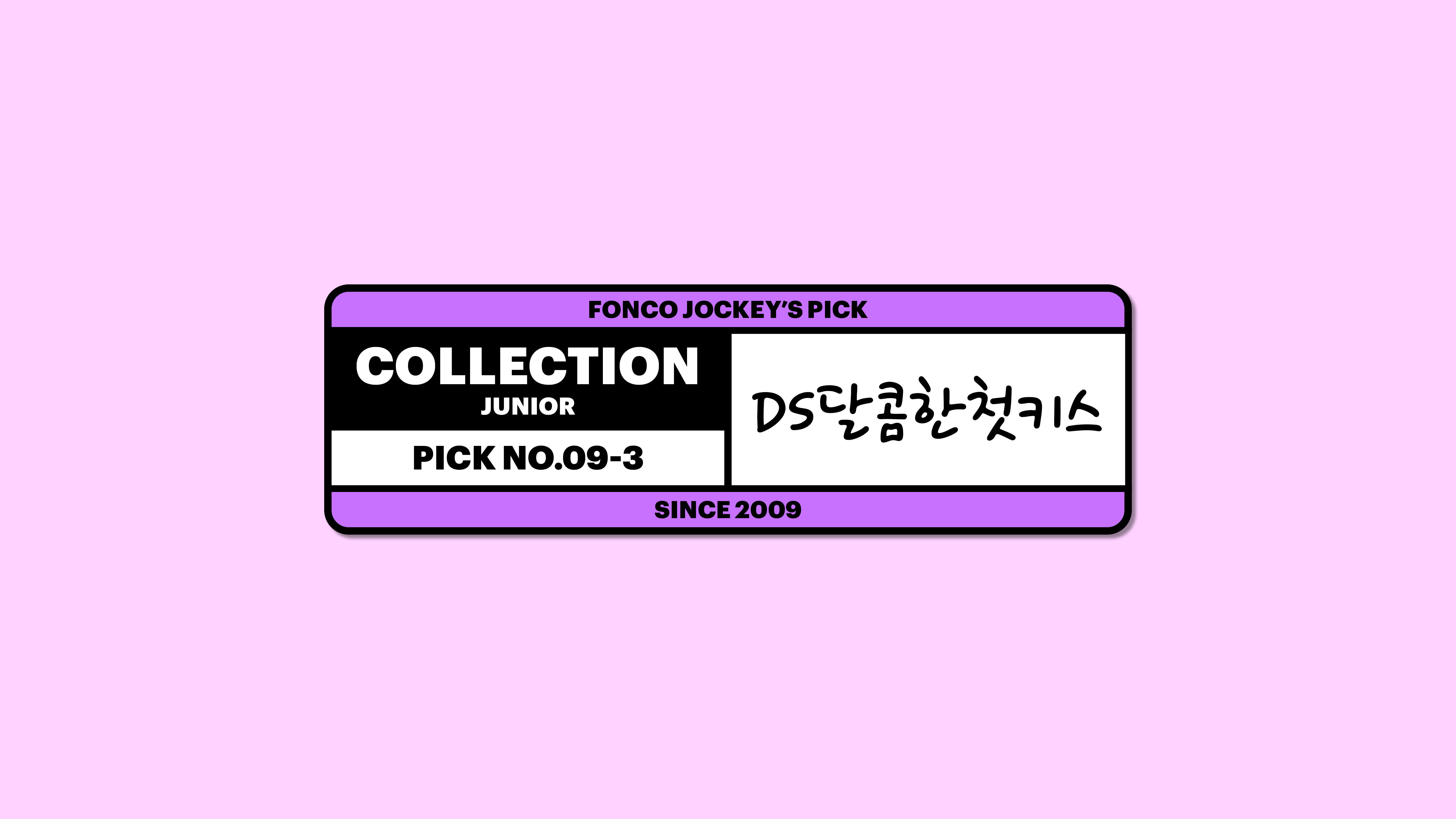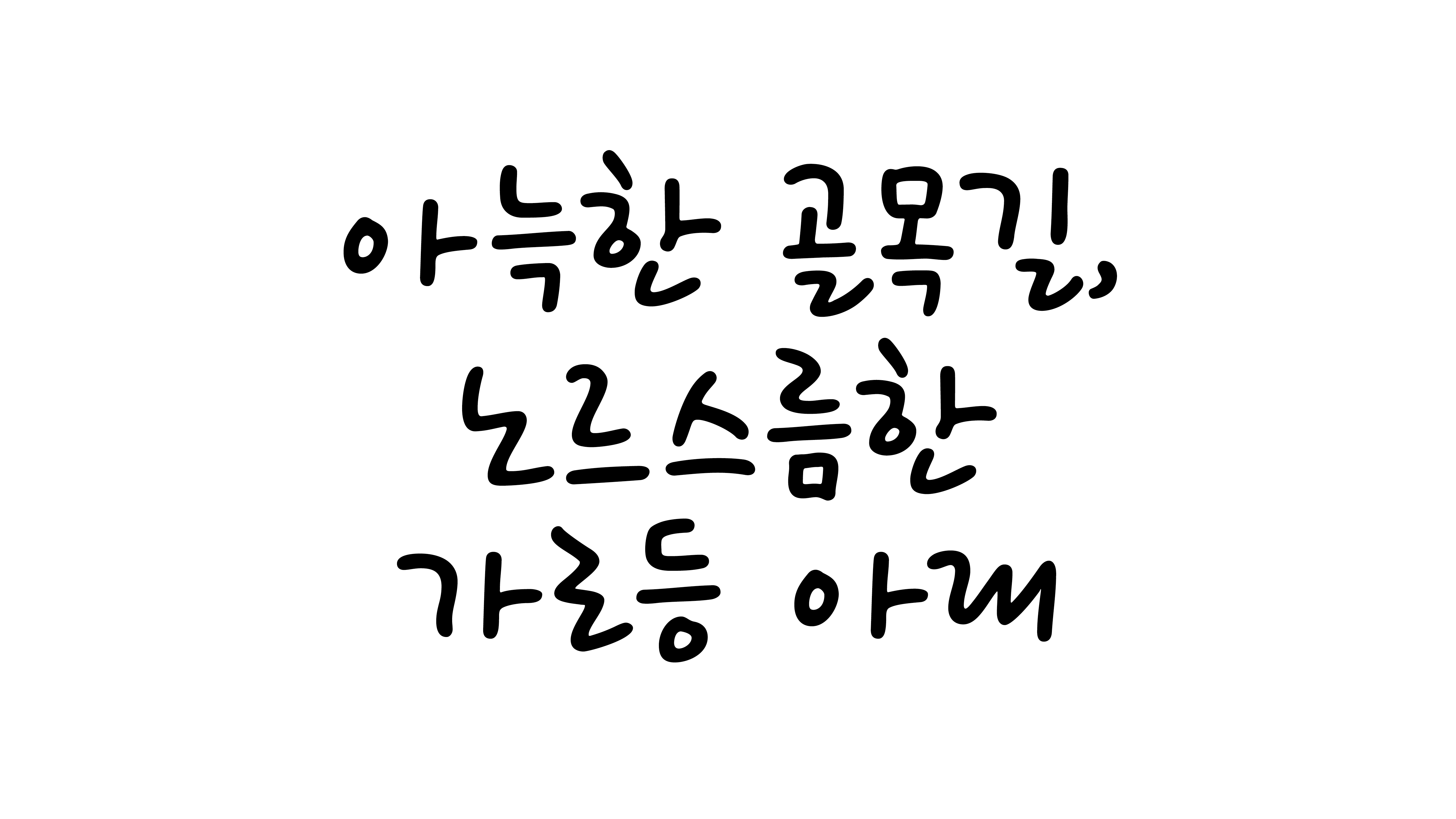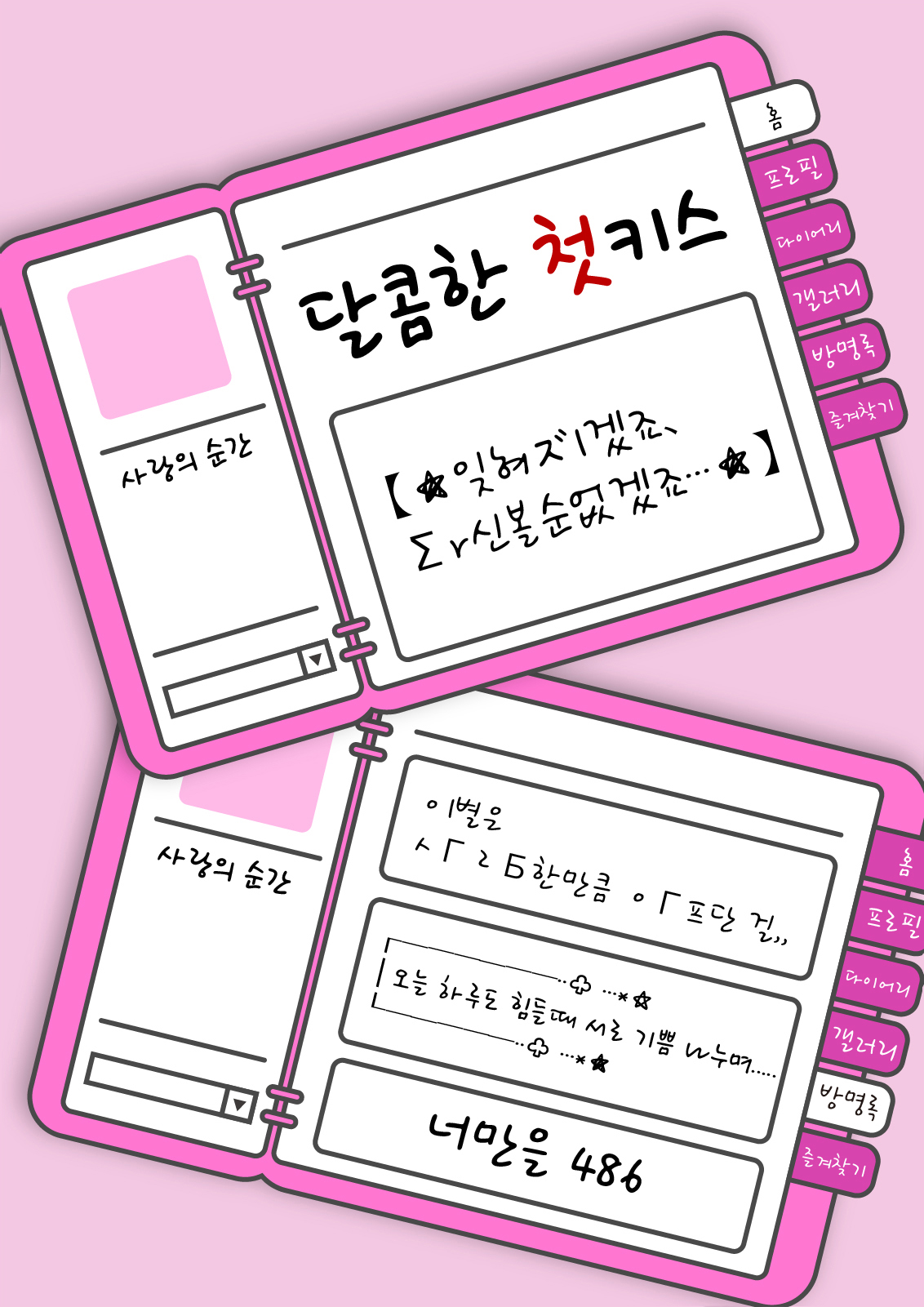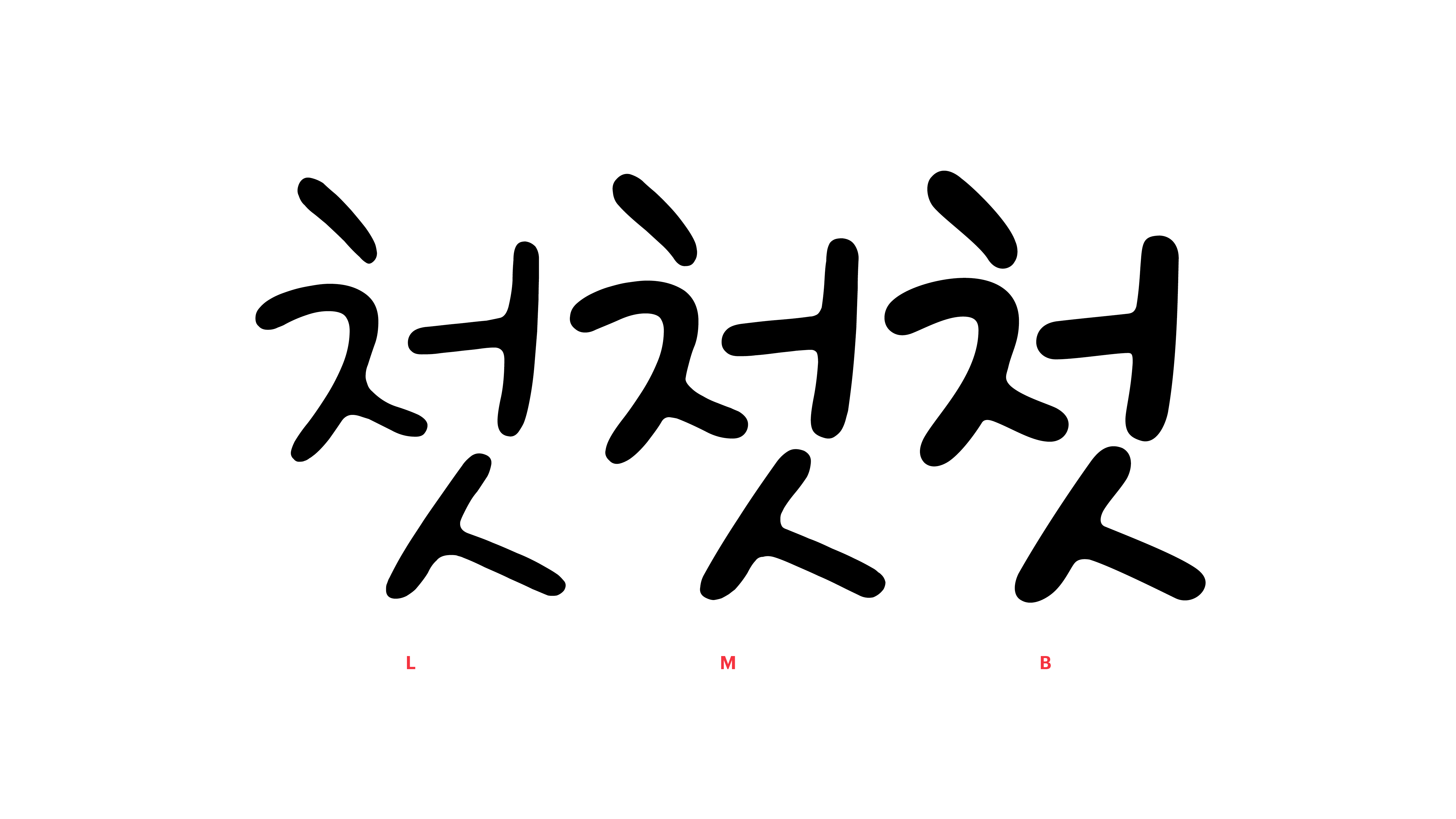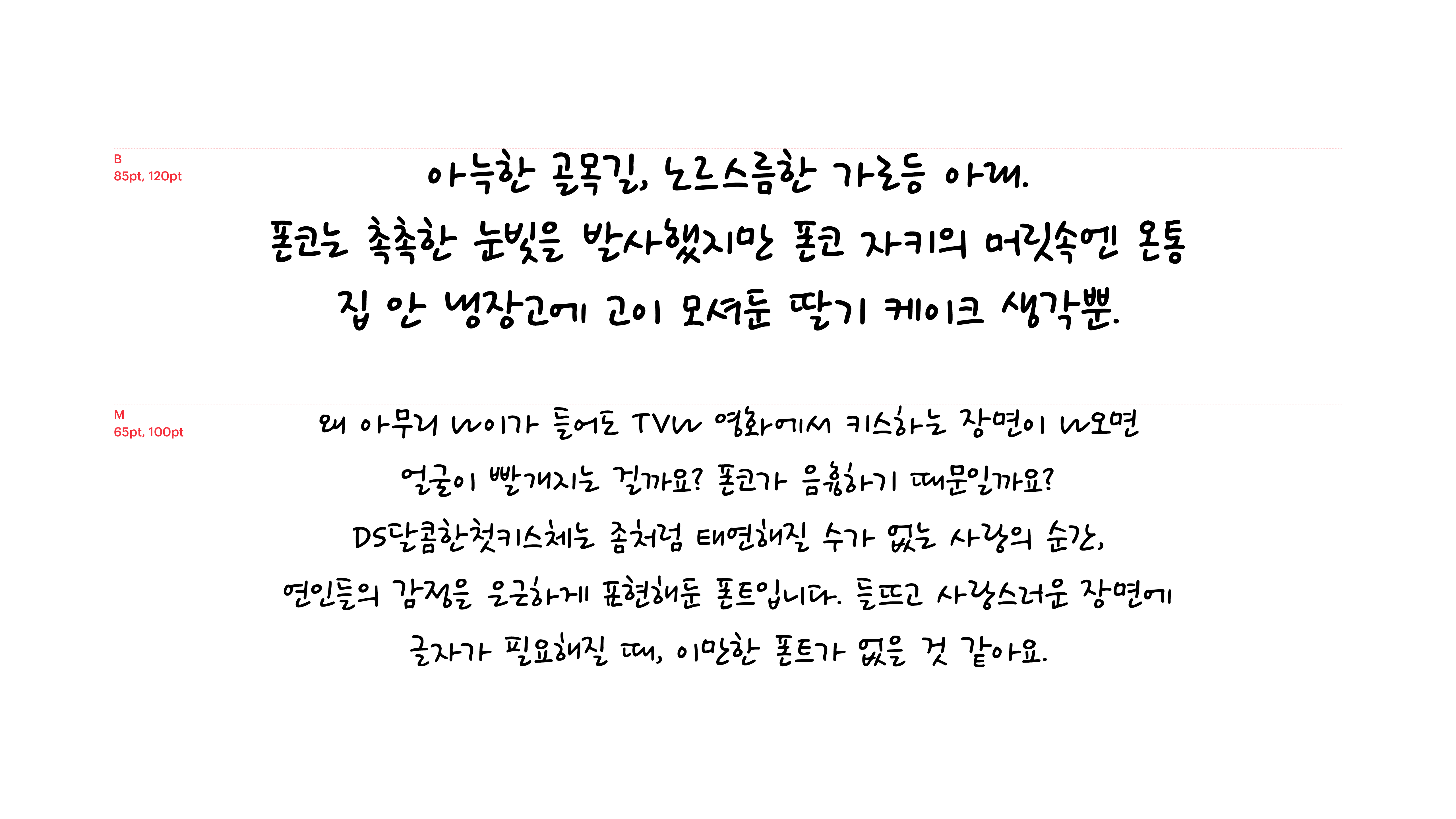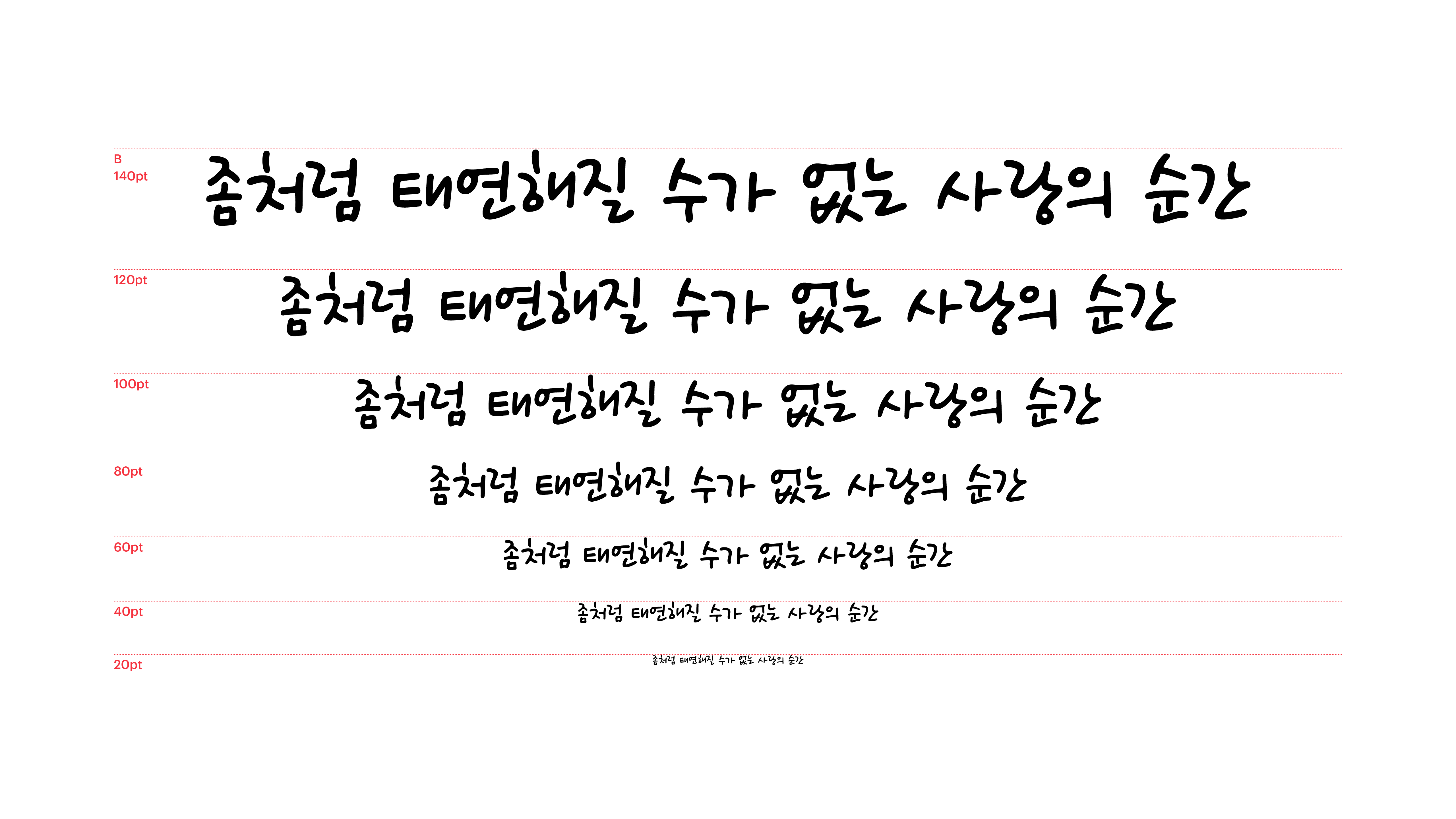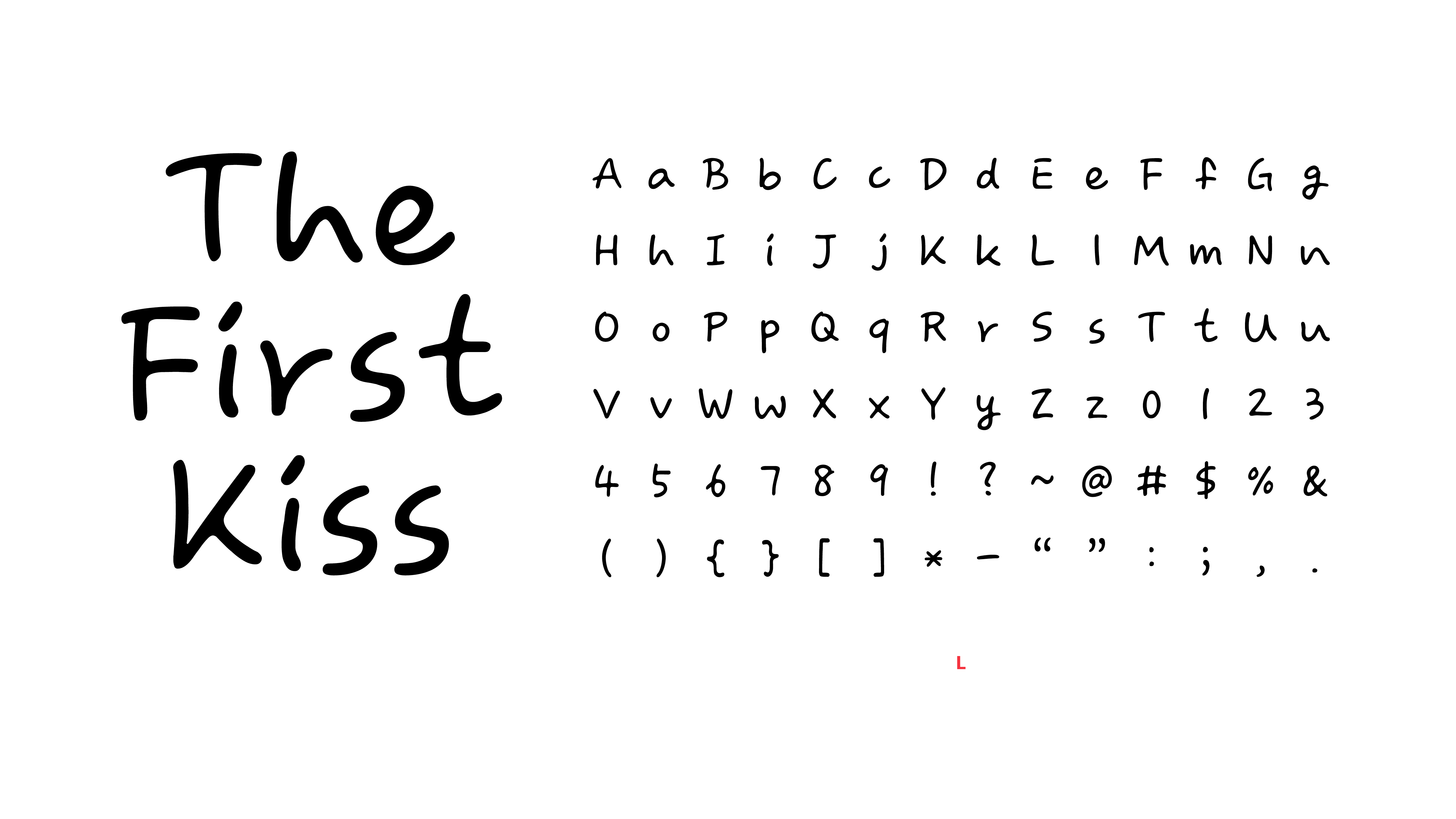
DS달콤한첫키스
Yoon DS달콤한첫키스
왜 아무리 나이가 들어도 TV나 영화에서 키스하는 장면이 나오면 얼굴이 빨개지는 걸까요? 폰코가 음흉하기 때문일까요? 달콤한첫키스체는 좀처럼 태연해질 수가 없는 사랑의 순간, 연인들의 감정을 은근하게 표현해둔 폰트입니다. 들뜨고 사랑스러운 장면에 글자가 필요한 순간, 이만한 폰트가 없을 것 같아요.